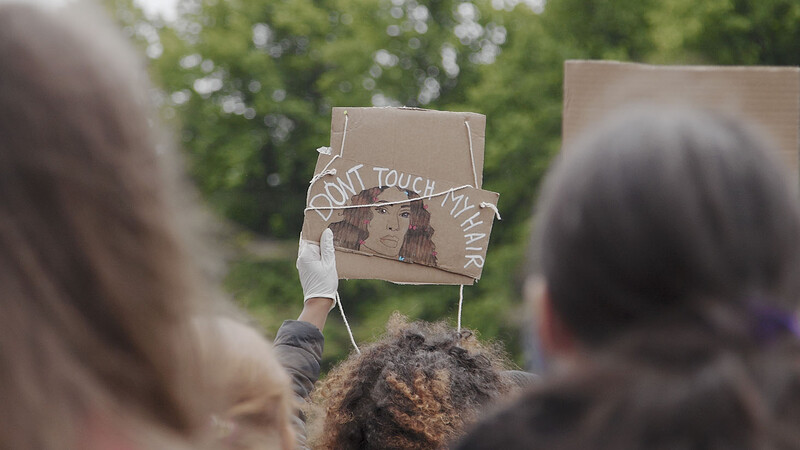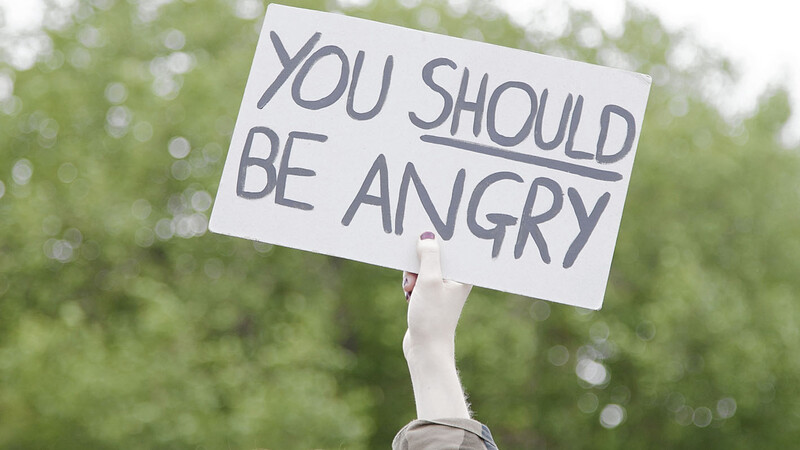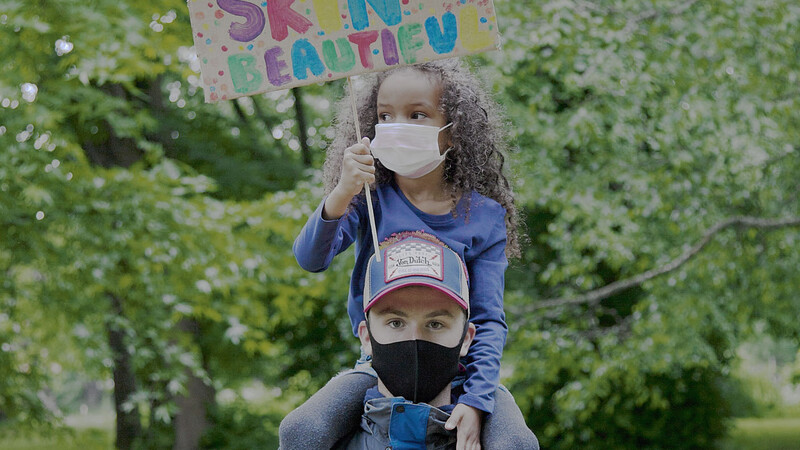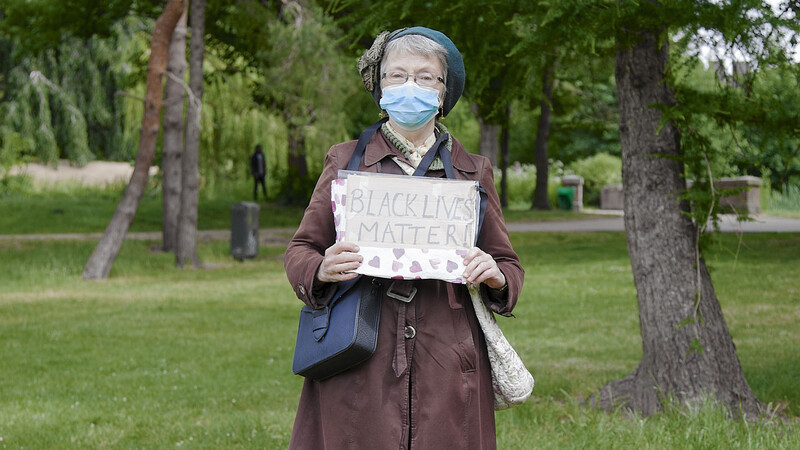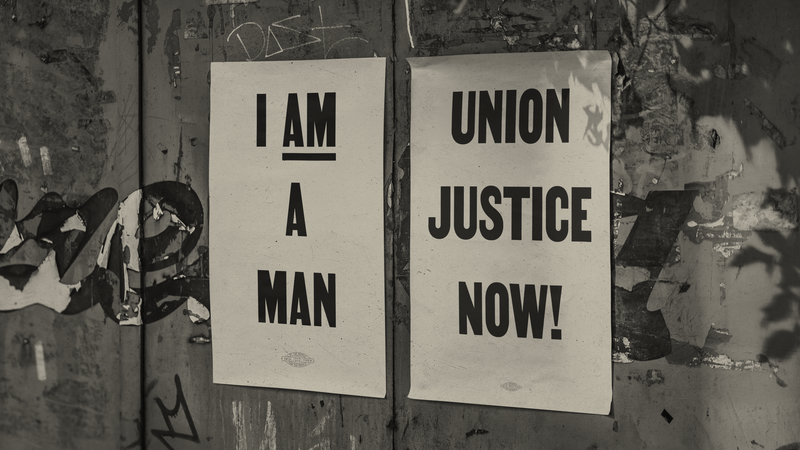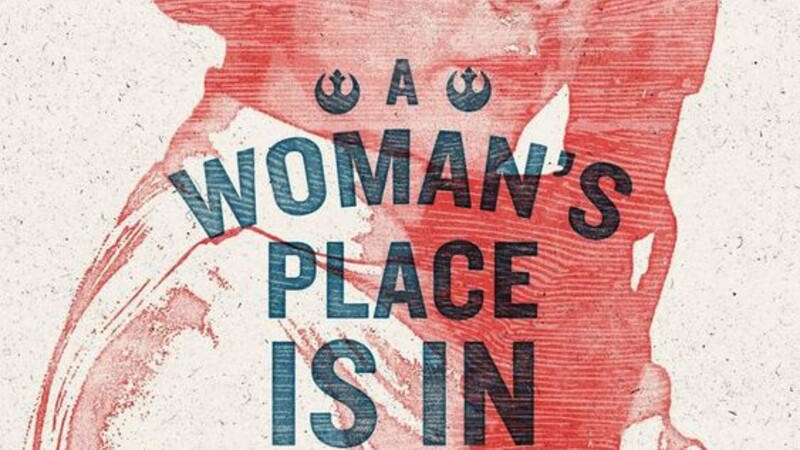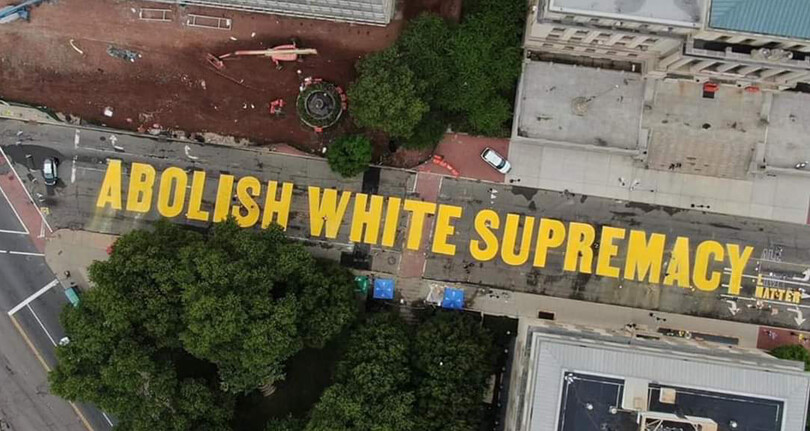
La tipografía y las protestas modernas
Mensajes contundentes: La tipografía y las protestas modernas.
La tipografía y las protestas modernas
En esencia, los tipos narran historias. Las formas de las letras transmiten un mensaje. Y dichos mensajes quizás encuentren su máxima expresión en los diseños para protestas liderados por la comunidad.
“ Nada captura la pasión y la espontaneidad de la protesta como los carteles hechos a mano. En ocasiones, el carácter urgente de las protestas nos obliga a coger un rotulador y ponernos a escribir. ”
Aunque es posible que muchas de las personas que elaboran carteles y pancartas para marchas y manifestaciones no se consideren especialistas en diseño gráfico, se convierten precisamente en eso en el momento en el que colocan letras en un soporte. Cada cartel es el reflejo de una historia más larga y contiene un mensaje que es sumamente personal y que, al mismo tiempo, expresa los pensamientos de un movimiento más amplio. Se crean desde la ira y la tristeza, y capturan la esencia de lo que representa el mejor diseño: impulsar el cambio.
«Acabar con las falsas distinciones».
La historia y el desarrollo de las tecnologías de fuentes e impresión han desempeñado un papel crucial en la forma en la que se crean los materiales de protesta y se difunden los mensajes. Durante la segunda mitad del siglo XX, herramientas como las prensas de serigrafía se hicieron más accesibles que nunca y ofrecieron la combinación perfecta entre arte y activismo.
“ Aunque es posible que muchas de las personas que elaboran carteles y pancartas para marchas y manifestaciones no se consideren especialistas en diseño gráfico, se convierten precisamente en eso en el momento en el que colocan letras en un soporte. ”
Algunos sitios se hicieron famosos al aceptar encargos rápidos y económicos para campañas, como el Poster Workshop en Camden Road, Londres, que estuvo abierto desde 1968 hasta 1971. El colectivo, que ofrecía sus instalaciones a huelguistas, grupos de derechos civiles y movimientos de liberación, como el grupo London Squatters Campaign, dirigía el taller con el propósito de fomentar respuestas a una gran variedad de temas políticos y globales, como los derechos laborales, el conflicto de Irlanda del Norte y la guerra de Vietnam.
Los estilos de diseño, así como los métodos para elaborar los diseños finales, también forman parte de un linaje histórico. Consideremos los movimientos feministas de los años 60 y 70: muchas imágenes parecen inspirarse directamente en las comunicaciones del movimiento por los derechos civiles que tuvo lugar en la misma época. La artista Lucia Vernarelli usaba un estilo xilográfico en sus láminas similar al que empleaba Emory Douglas en sus diseños para el Partido Pantera Negra.
Sin embargo, fuera de la industria creativa, no siempre es adecuado emplear la etiqueta «diseño» en el contexto de movimientos de protesta populares. La académica Dori Tunstall ha escrito mucho sobre cómo pueden aplicarse los principios de la antropología del diseño a la organización comunitaria. En un ensayo de 2016 publicado en el Feminist Organization’s Handbook de WCCW, afirma que es esencial para las personas «acabar con las falsas distinciones entre arte, artesanía y diseño» para contrarrestar las «jerarquías» que logran colarse incluso en el activismo comunitario.
Según Tunstall, «el activismo basado en el arte recibe mayor reconocimiento en la prensa y, muchas veces, más apoyo económico», seguido por el «activismo basado en la artesanía… debido a la percepción de autenticidad arraigada» y, finalmente, «el activismo basado en el diseño queda en último lugar, ya que se considera demasiado “profesional” para la base, pero demasiado “generalizado” para la expresión artística».
Señala que estas distinciones son principalmente parte del discurso europeo: en otras culturas, las personas simplemente crean sin plantearse qué son, o su lugar en «la lucha».
Democratizar el diseño: la comunidad por encima de la imagen de marca.
En la última década, estas distinciones se han ido desvaneciendo, por no decir que se han ido desarticulando casi por completo. Desde la llegada de la tecnología digital, la democratización de las herramientas de software creativas ha permitido que se afiance un enfoque más orientado a la comunidad y menos egocéntrico, y cada vez más diseñadores y diseñadoras crean obras de código abierto o que se pueden descargar gratis.
Una de las fortalezas del movimiento «Marcha de las Mujeres», por ejemplo, radica en su ausencia de marca o identidad visual específica, según lo definirían las «grandes agencias». El movimiento comenzó en Estados Unidos a principios de 2017, tras la investidura de Donald Trump, y desde entonces se ha convertido en una acción de resistencia global contra el presidente estadounidense y sus comentarios misóginos, afianzándose aún más en la sociedad y el gobierno por igual.
Algunas de las imágenes emblemáticas que han surgido de este movimiento son el cartel de Hayley Gilmore con la frase «A woman's place is in the resistance» («El lugar de una mujer está en la resistencia»), con llamativas letras mayúsculas sobre una imagen en color rojo, y el símbolo «Femme Fists» (puños de mujer en alto), de Deva Pardue.
Imagen de portada: Mural callejero, Newark, NJ. Escrito con el tipo de letra Martin de Vocal Type. Crédito de la fotografía: Isaac Jiménez.